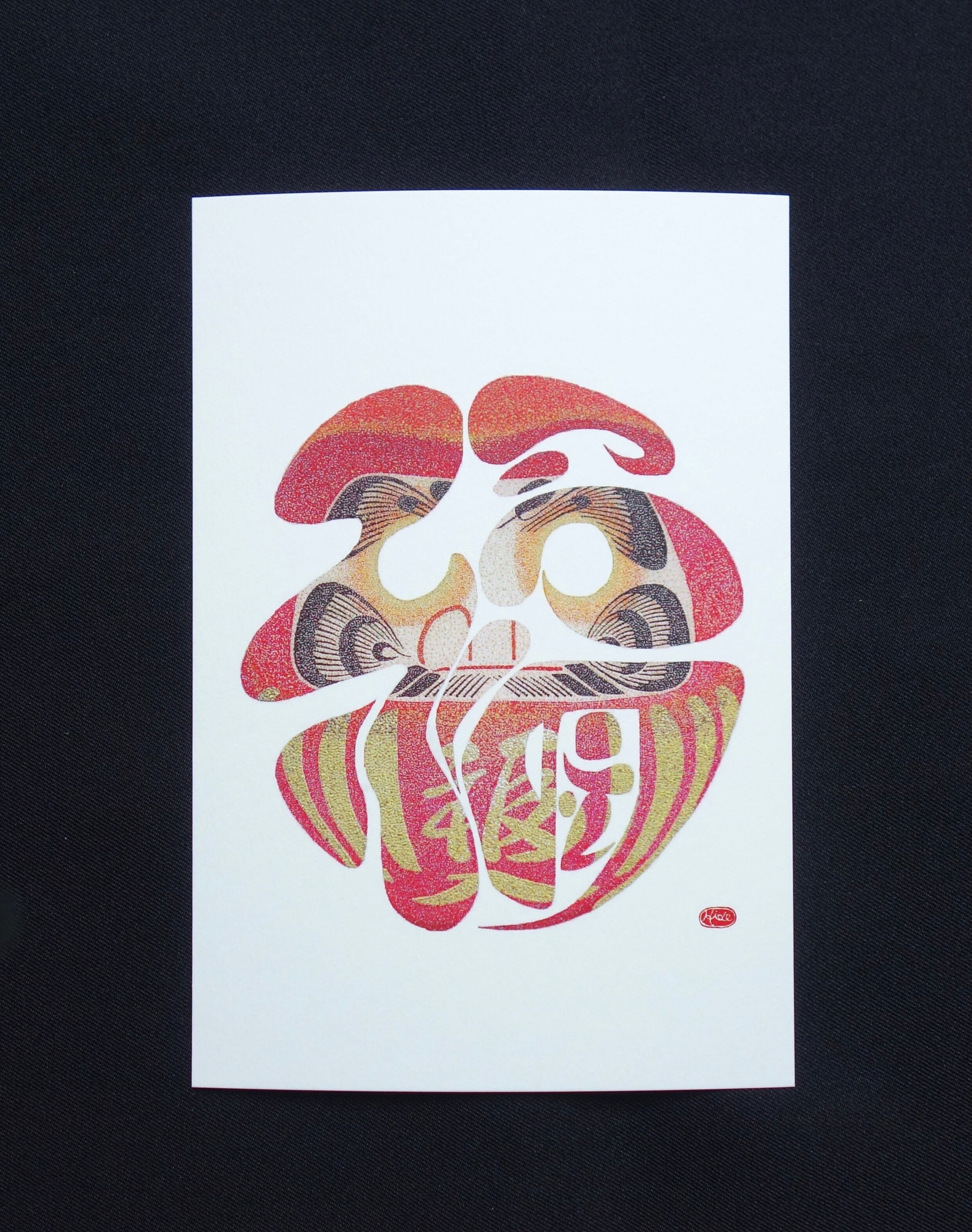
福~ふつうのこと~(福だるま)はがきサイズ
【福だるま】
だるまの形や色をした作品ですが、よく見るとひらがなの「ふつうのこと」で作られた
「福」のこころMojiになっています。
原画はA3サイズ・水彩・点描画。
『福』~ふつうのこと~
夢や目標を抱くことは大切なこと。
想いが強すぎると「重い」になってしまい身動きがとれなくなります。
普段通りの暮らしがおくれることは「運がいい」こと。
それに気がつくと「幸福」になります。
何か特別なことではなく、何も起きないことがどれほど幸せであるか。
毎日がただ淡々と過ぎていくことが、「幸せの本質」かもしれません。